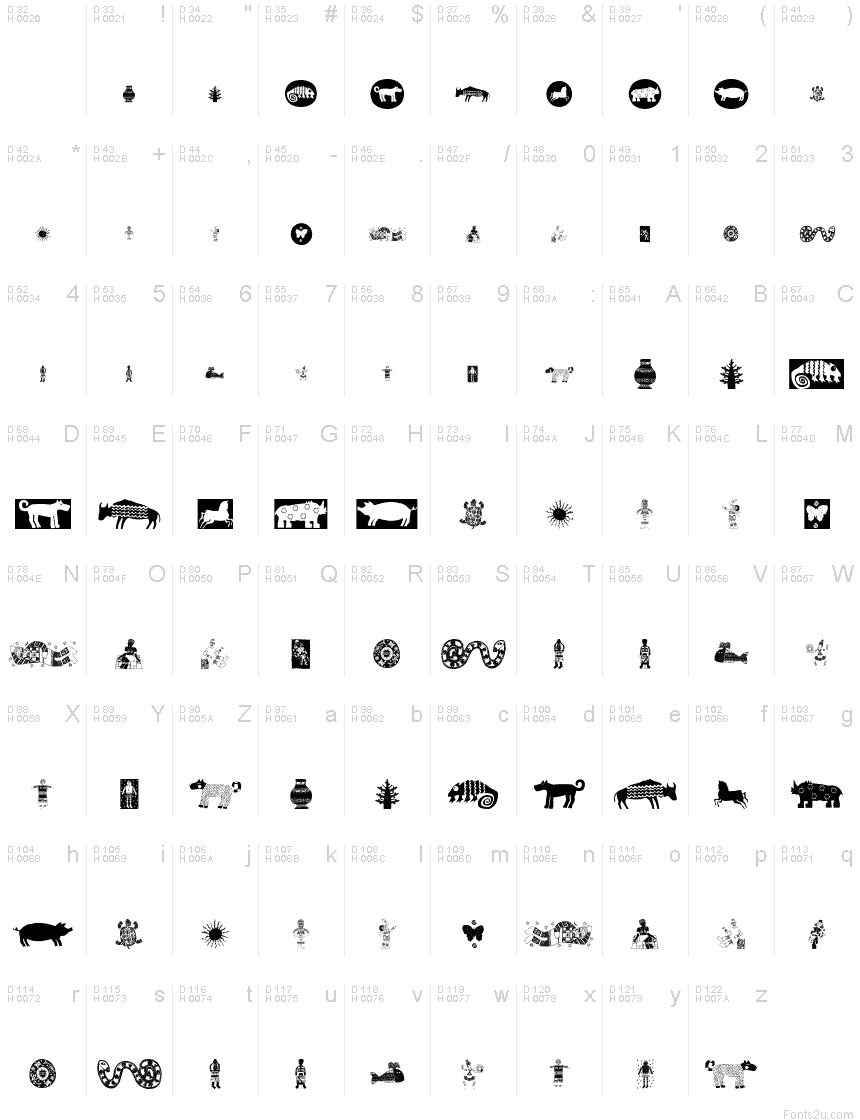
Africain von M. Klein ist eine kostenlose Tribal-Dingbat-Schrift, die eine ganze Reihe kräftiger, tiefschwarzer Illustrationen direkt auf Ihre Tastatur bringt. Jede Glyphe wirkt wie ein kleiner Holzschnitt: gemusterte Gefäße, zeremonielle Figuren, Schilde, Tiere und Textilien, dargestellt in markanten schwarzen Silhouetten mit dichten ornamentalen Details. Die Icons besitzen eine handgeschnitzte, leicht raue Kante, die dem Layout eine haptische, handgefertigte Energie verleiht – weit weg vom flachen Clip-Art-Look.
Mit Africain lassen sich im Handumdrehen reichhaltige visuelle Umrandungen, Abzeichen und Motive für Festivalplakate, Branding für kulturelle Veranstaltungen, Buchcover, Arbeitsblätter, Verpackungen sowie Reise- oder Geschichtsmagazine erstellen. Diese kostenlose Schrift glänzt besonders, wenn die Icons groß genug eingesetzt werden, um die feinen Muster zur Geltung zu bringen; kombinieren Sie sie mit einer schlichten geometrischen Sans Serif, um das Typografie-Design klar zu halten, während die Illustrationen für die erzählerische Tiefe sorgen.